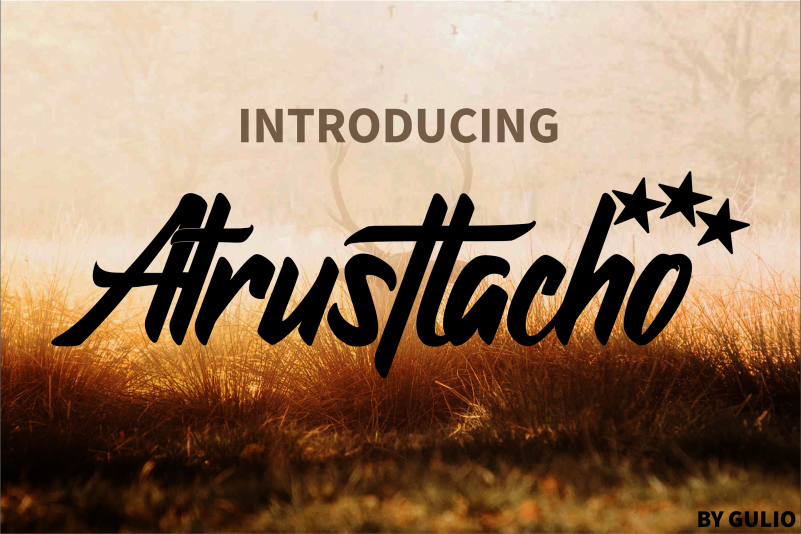
Atrusttacho Awesome Font – Fonte Grátis
Atrusttacho Awesome Font
AtrásTacho é uma fonte elegante, com uma inclinação única que mantém consistência ao longo do texto. Esta característica se destaca especialmente na letra A, que possui ligaduras criadas entre a minúscula de ‘a’ até a ‘z’. AtrásTacho combina facilmente em projetos visuais diversos como identidades empresariais, revistas e brochuras, materiais de marketing impressos, banners para websites, desenhos de roupas e outros trabalhos gráficos. Sujeitosa aos requisitos dos mais exigentes designers, esta fonte é uma escolha ótima. AtrásTacho foi projetada pelo designer GulioSt e oferece um toque singular que certamente deixará seu design mais notável.
Designer: GulioSt